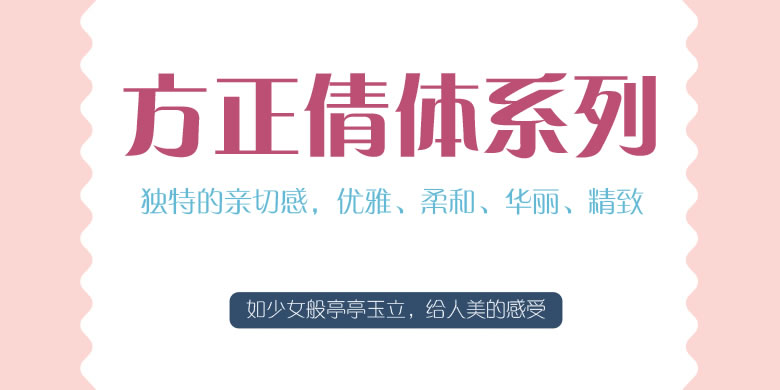
方正倩体系列包含以下字体
方正倩体是以扁平马克笔的书写轨迹为基础设计的。其笔画衔接和转折均为圆弧形,笔形和字形的设计注重对称均衡。方正倩体家族包含3款字重:方正粗倩笔画对比强烈,端庄大气;方正中倩笔画粗细适中,婉转妩媚;方正细倩笔画纤秀,文静清雅。适用于女性类服饰、日化、家居品牌的广告和产品包装设计。